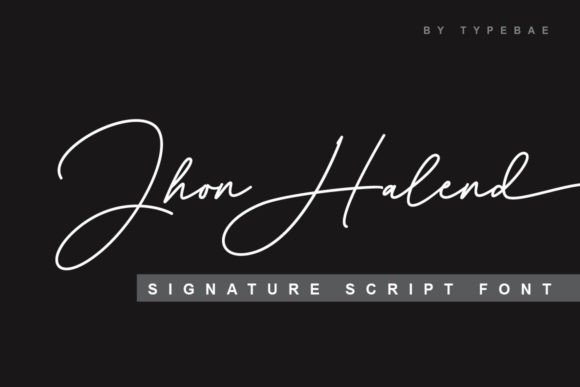
Jhon Halend
適切なデザイン要素を見つけるのは難しい場合がありますが、Jhon Halendは作品を即座に引き立てる優れたコレクションを提供します。
POD(オンデマンド印刷)製品、結婚式の招待状、またはソーシャルメディアのグラフィックを作成している場合でも、Jhon Halendは理想的です。